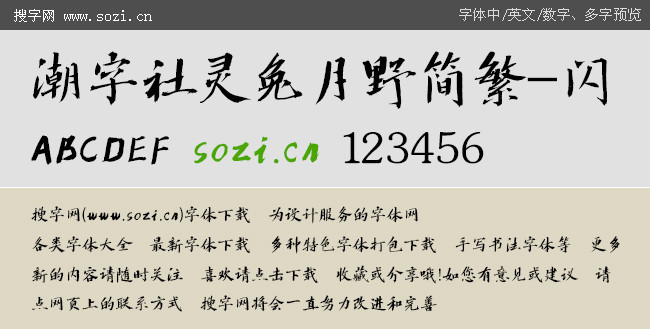
潮字社靈兔月野簡繁-閃
搜字網(wǎng)提供一款潮字社靈兔月野簡繁-閃中文字體下載,潮字社靈兔月野體以楷書為基準(zhǔn),同時(shí)又有行書筆畫的牽絲連帶、草書的張揚(yáng)瀟灑,顯得靈動(dòng)自然,給人以邊塞疆場的廣袤、遼闊、磅礴之感。整體造型統(tǒng)一,又將一些單字筆畫極盡夸張,形成強(qiáng)烈對(duì)比,表現(xiàn)出一種狂放不羈氣質(zhì)。適合應(yīng)用于藝術(shù)設(shè)計(jì)、平面宣傳設(shè)計(jì)、網(wǎng)頁設(shè)計(jì)等領(lǐng)域等應(yīng)用。(本字體為個(gè)人非商用版,商用請(qǐng)聯(lián)系作者購買授權(quán))